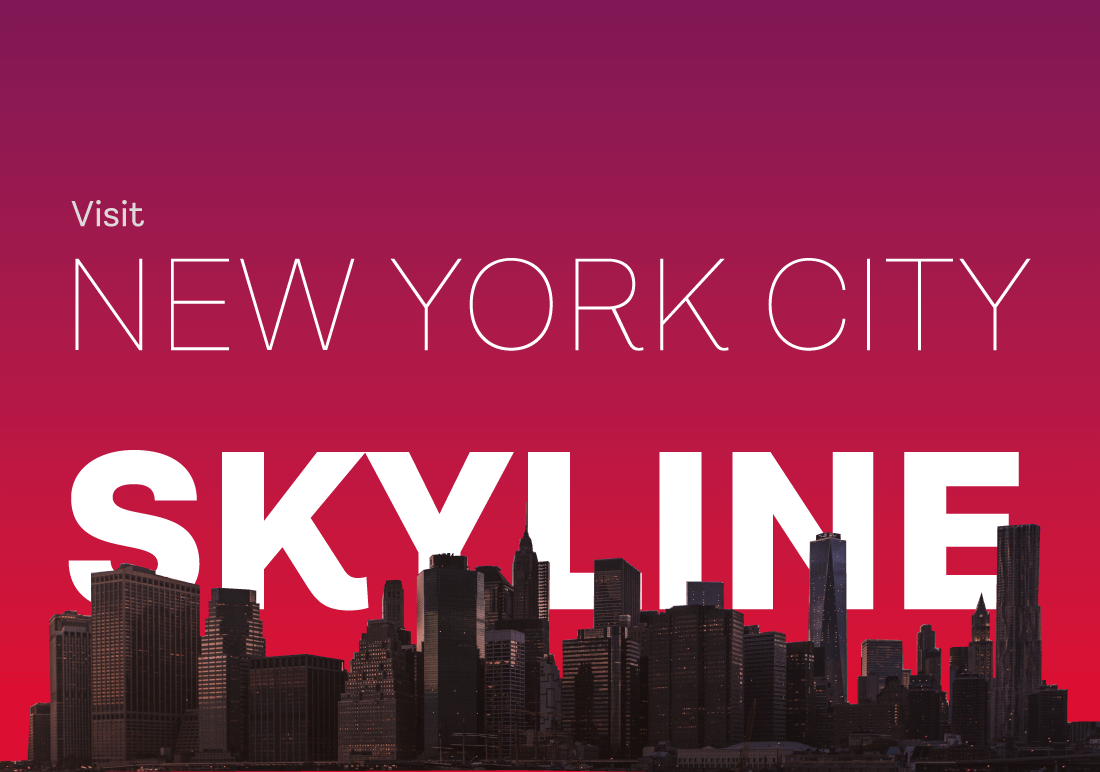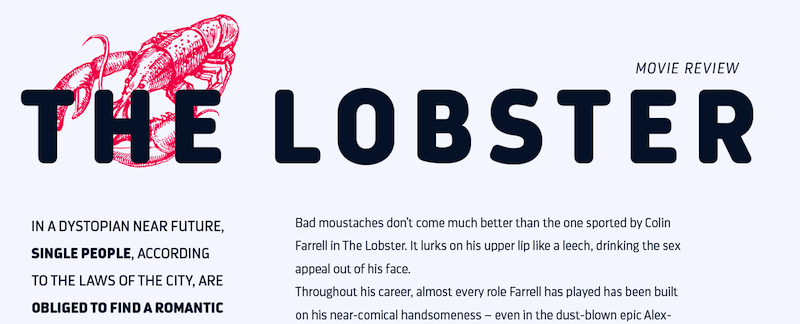
Monotonisches Griechisch und Kyrillisch, Lang-S und Versaleszett.
"The typefaces include small capitals for Cyrillic and Latin alphabets, 33 ligatures, standard and old-style figures, and stylistic alternates. "
Mir gefällt die Schrift, weil sie auf mich "kernig-markant" aber dennoch elegant wirkt.
Finde die Schrift ganz harmonisch und günstig...weiß aber nicht  wie gut sie "ausgebaut" ist.
Die hat leider keine richtige Italic, nur Oblique – schade ... :-(
Und das VE wirkt m. E. etwas mager
Und muss man hier was zum VE sagen :shock::-?
Sonst ist die doch ganz hübsch, das VE wäre für mich auch kein Grund sie komplett abzulehnen. Ich würde einfach so tun, als hätte sie gar keins :roll:
Aber das R ist grenzwertig – es hat nicht nur einen Knick, sondern auch einen Wasserkopf den ich persönlich schlimmer finde ...
In der Regular fällt das noch mehr auf als in der Medium.